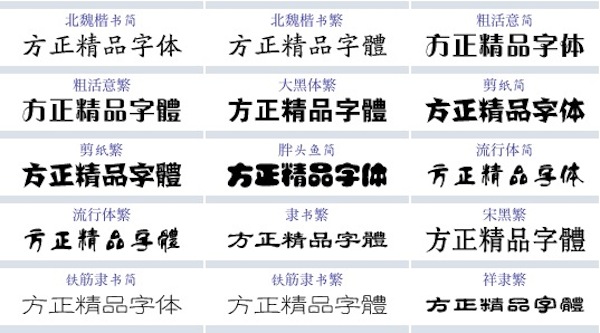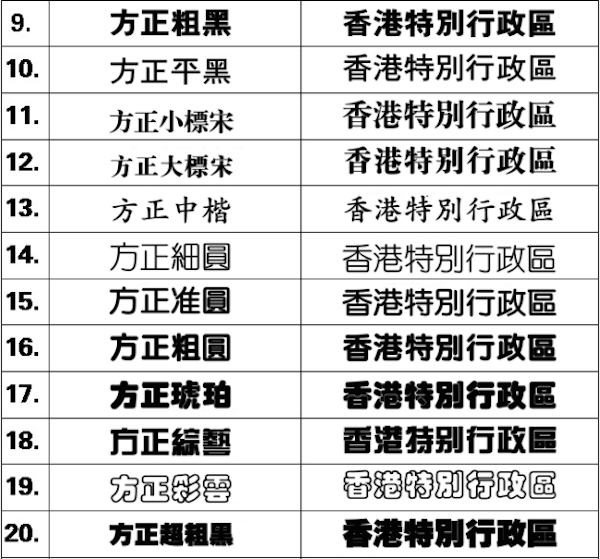
方正字体是北京北大方正电子有限公司开发的中文字体。
方正字体品质精良,通过ISO9001质量体系认证,符合国家颁布的字形规范,曾于1995年、1997和2001年三次通过由国家新闻出版署,国家语言文字工作委员会,全国印刷字体工作委员会联合主持的鉴定。
方正字体产品全面支持方正系统和第三方系统,前端显示和后端输出保持一致,做到“所见即所得”,产品系列化、标准化、通用化,开放性产品跨平台使用。方正字库字款丰富、字形美观、性能稳定、适应面广,运行速度快,且存贮容量小。全面支持GB、GBK、GB18030、BIG-5以及JIS、KSC等编码体系,可以提供TrueType,PostScript Type1、Type0、CID等各种通用格式字库。
方正GBK字体现在为印刷出版业标准字库,下面列举部分方正GBK字体:
方正报宋_GBK、方正超粗黑_GBK、方正粗倩_GBK、方正粗宋_GBK
方正彩云_GBK、方正大标宋_GBK、方正大黑_GBK、方正仿宋_GBK
方正黄草_GBK、方正华隶_GBK、方正琥珀_GBK、方正黑体_GBK
方正康体_GBK、方正少儿_GBK、方正楷体_GBK、方正隶二_GBK
方正隶变_GBK、方正隶书_GBK、方正美黑_GBK、方正新报宋_GBK
方正新舒体_GBK、方正平和_GBK、方正胖娃_GBK、方正宋三_GBK
方正宋黑_GBK、方正瘦金书_GBK、方正书宋_GBK、方正舒体_GBK
方正宋一_GBK、方正水柱_GBK、方正魏碑_GBK、方正小标宋_GBK
方正细等线_GBK、方正细黑一_GBK、方正行楷_GBK、方正细倩_GBK
方正细珊瑚_GBK、方正细圆_GBK、方正准圆_GBK、方正粗圆_GBK
方正姚体_GBK、方正幼线_GBK、方正中等线_GBK、方正稚艺_GBK
方正中倩_GBK、方正综艺_GBK、方正卡通_GBK、方正古隶_GBK
方正小篆体_GBK、方正启体_GBK、方正硬笔楷书_GBK、方正毡笔黑_GBK
方正硬笔行书_GBK、方正铁筋隶书_GBK、方正北魏楷书_GBK、方正祥隶_GBK
方正粗活意_GBK、方正流行体_GBK、方正剪纸_GBK、方正胖头鱼_GBK